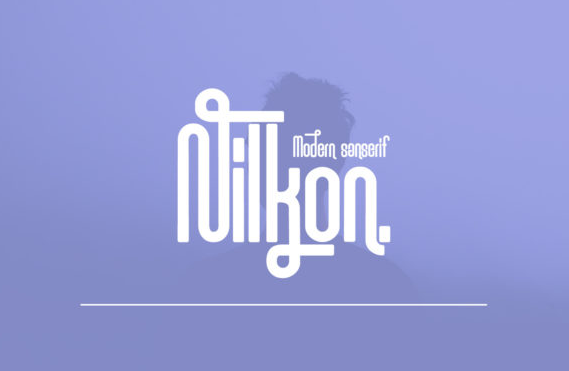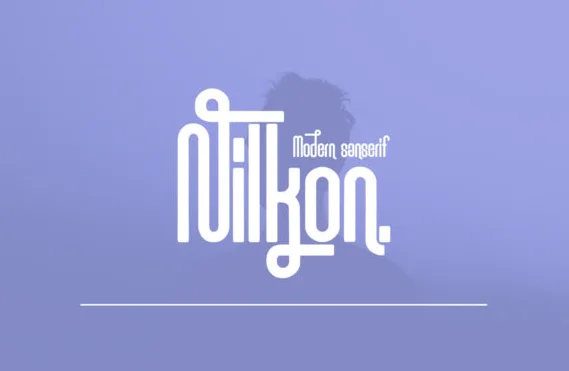
Название: Nilkon Font (2021)
Nilkon - это классный, современный и выразительный шрифт.
Этот шрифт идеально подходит для написания веб-дизайнов, визитных карточек и практически всего, что требует уникального штриха.